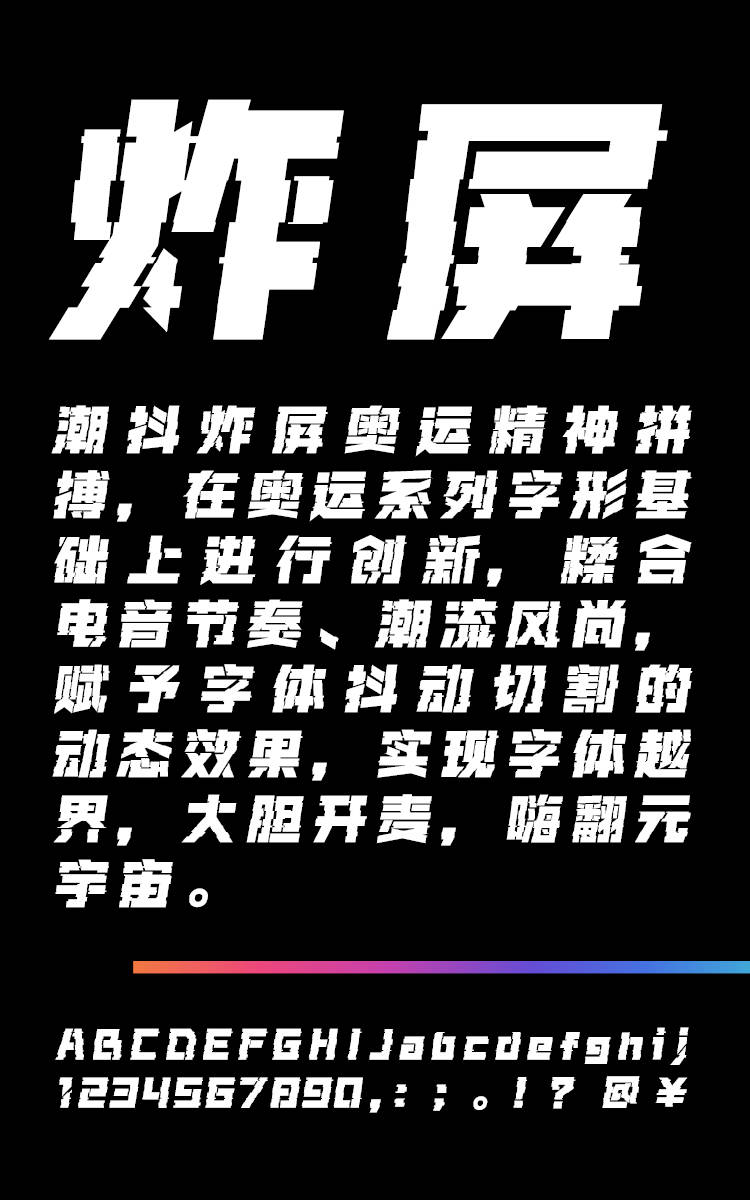
潮抖炸屏奥运精神拼搏 爆
潮抖炸屏奥运精神拼搏 爆,这款字体结构工整、笔画清晰,兼顾美观与易读性,适用于标题、正文、海报、包装、LOGO 等多种场景。字形优雅稳定,风格百搭耐看,适配日常排版与创意设计,让文字呈现更舒适、更具质感。潮抖炸屏奥运精神拼搏 爆一笔一画,皆是细节,以均衡的比例、流畅的线条打造舒适视觉体验,字形端正大气,风格简约现代。无论是商业设计、品牌宣传还是日常排版,都能轻松驾驭,让文字更有格调与力量。潮抖炸屏奥运精神拼搏 爆字体下载。
潮抖炸屏奥运精神拼搏 爆字体介绍
潮抖炸屏奥运精神拼搏 爆字样展示
潮抖炸屏奥运精神拼搏,在奥运系列字形基础上进行创新,糅合电音节奏、潮流风尚,赋予字体抖动切割的动态效果,实现字体越界,大胆开麦,嗨翻元宇宙。